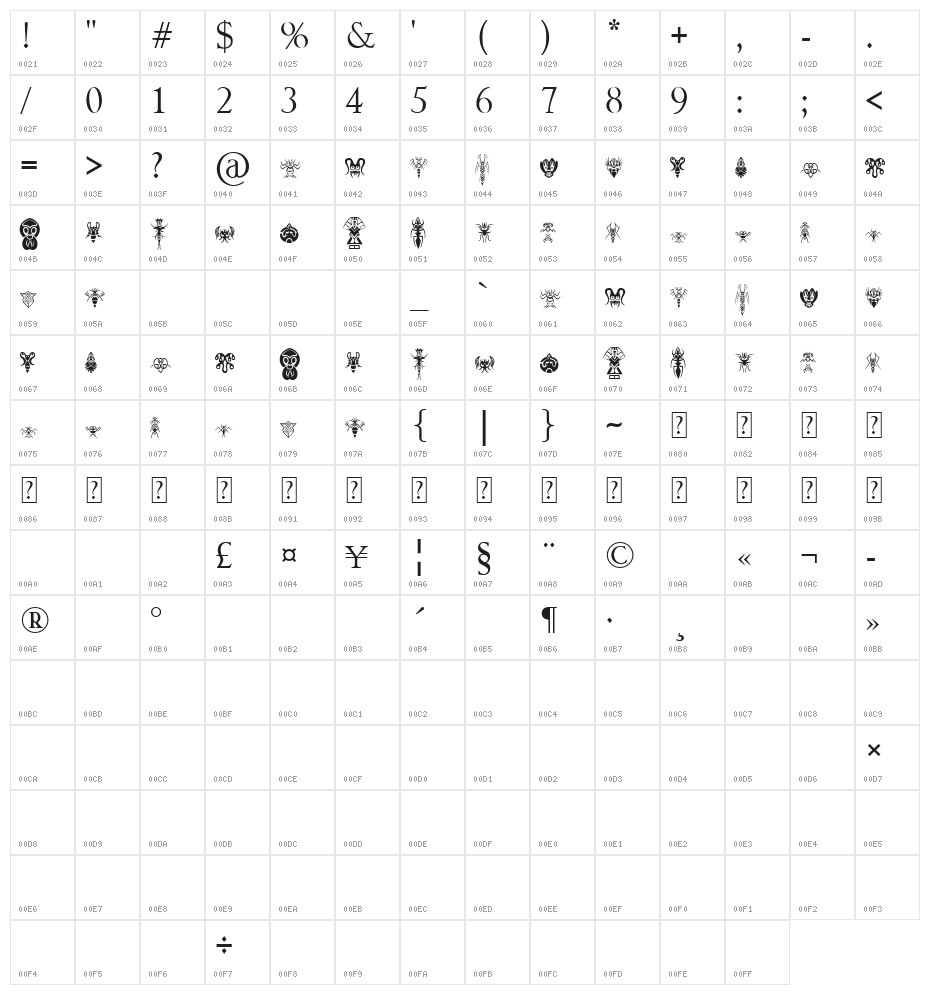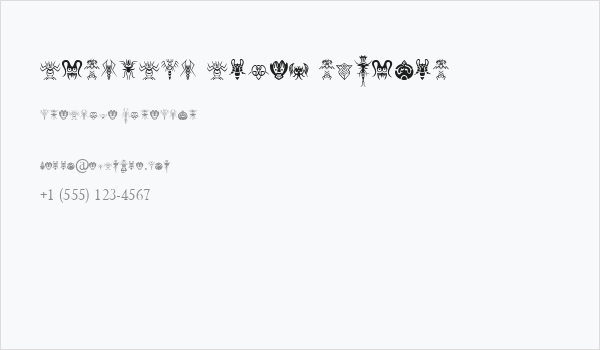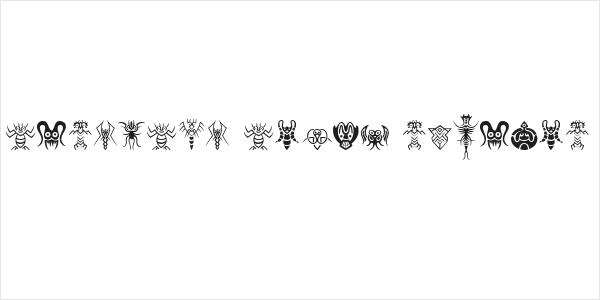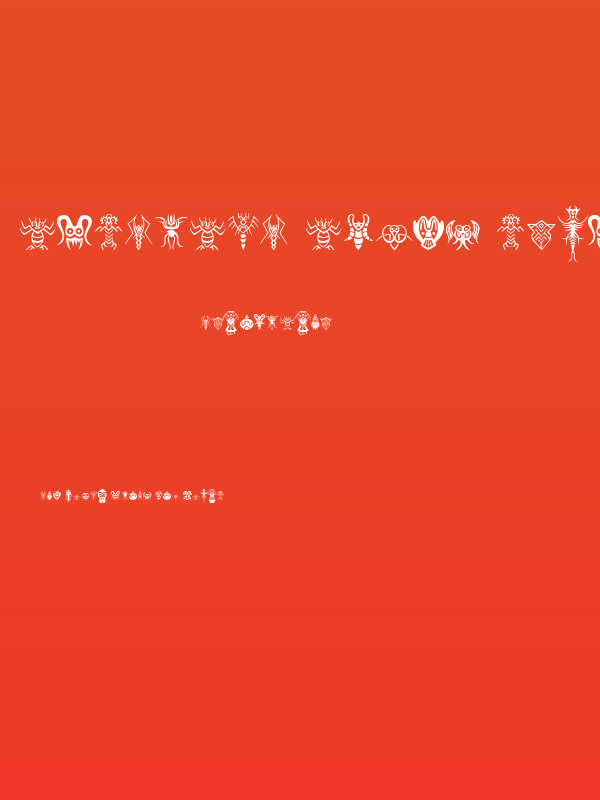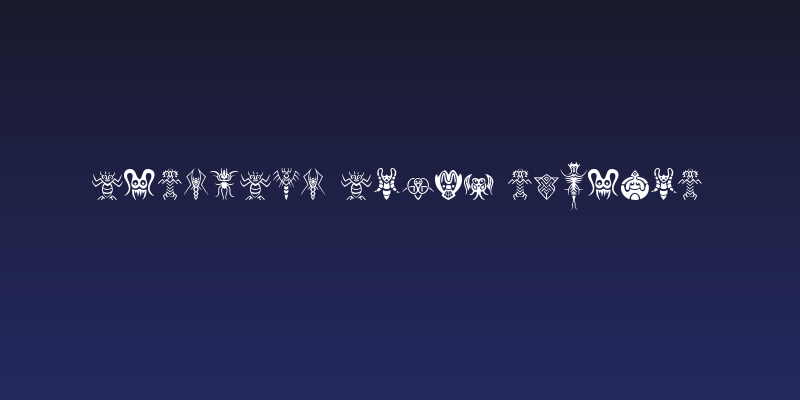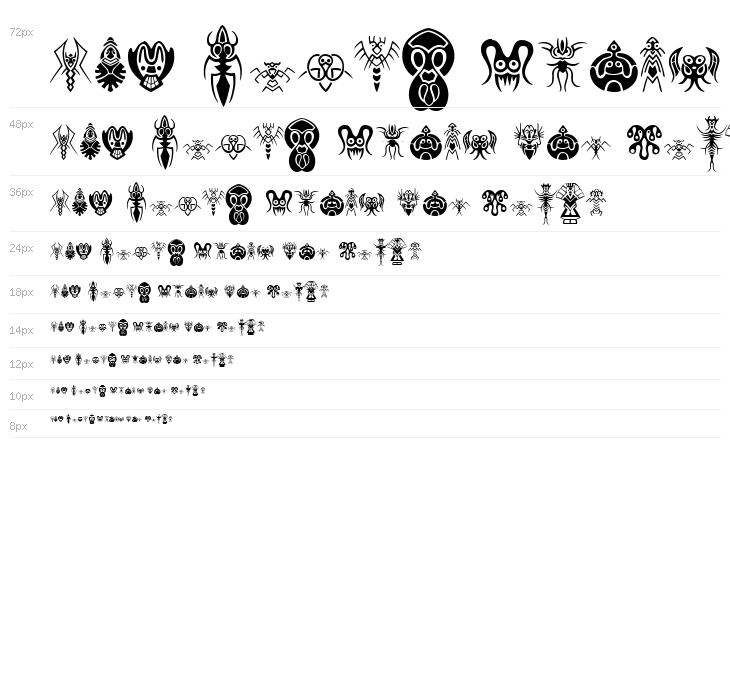
Abstract Alien Symbols Font
ABSTRACT-ALIEN-SYMBOLS MAIUSCOLE
ABSTRACT-ALIEN-SYMBOLS MINUSCOLO
ABSTRACT-ALIEN-SYMBOLS ALTRI CARATTERI
| Caso d'uso | Logos, Artistic designs, Game graphics |
| Progetti proposti | Ideal for use in science fiction artwork, game design, or as decorative elements in graphic design projects. |